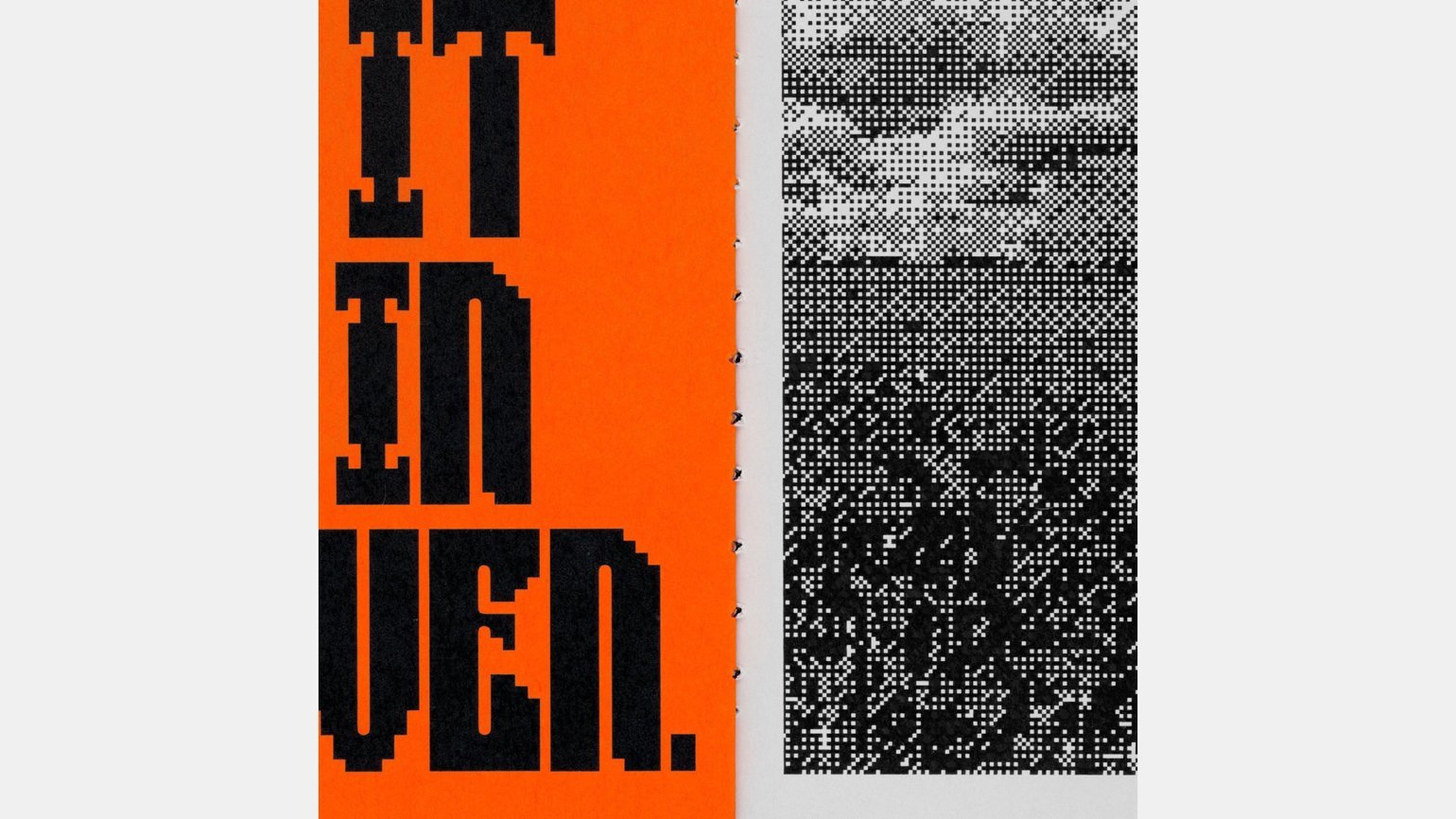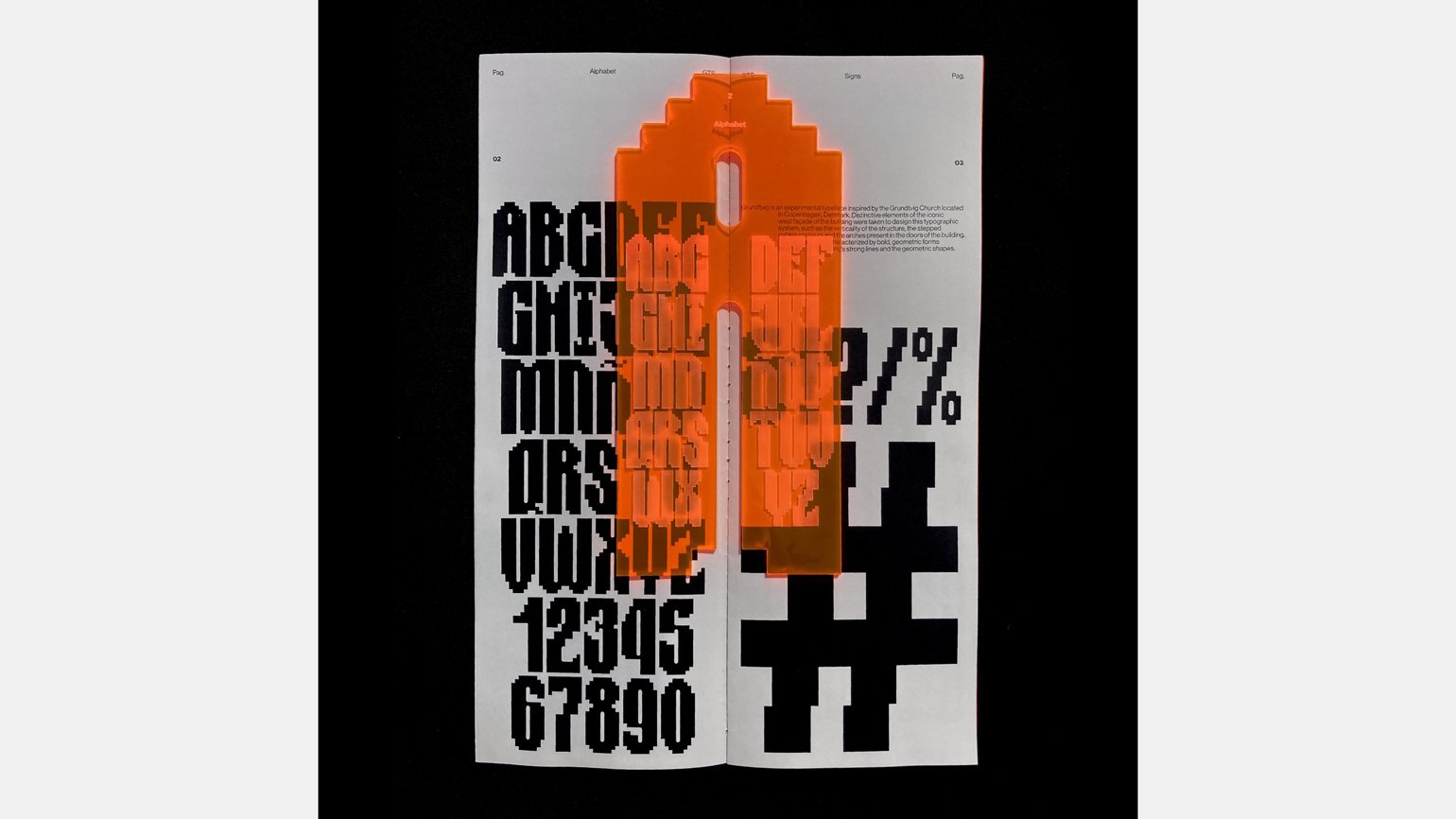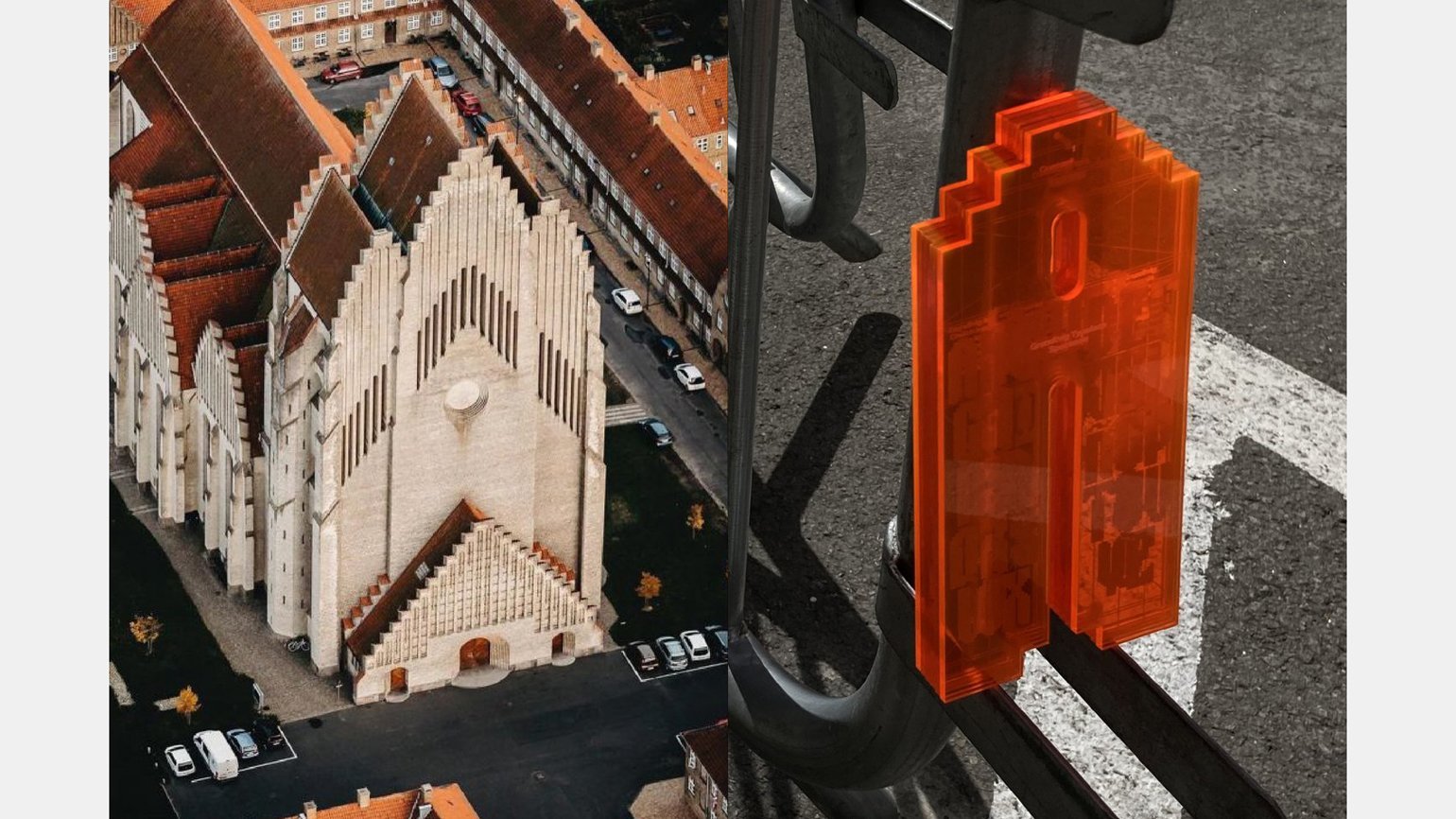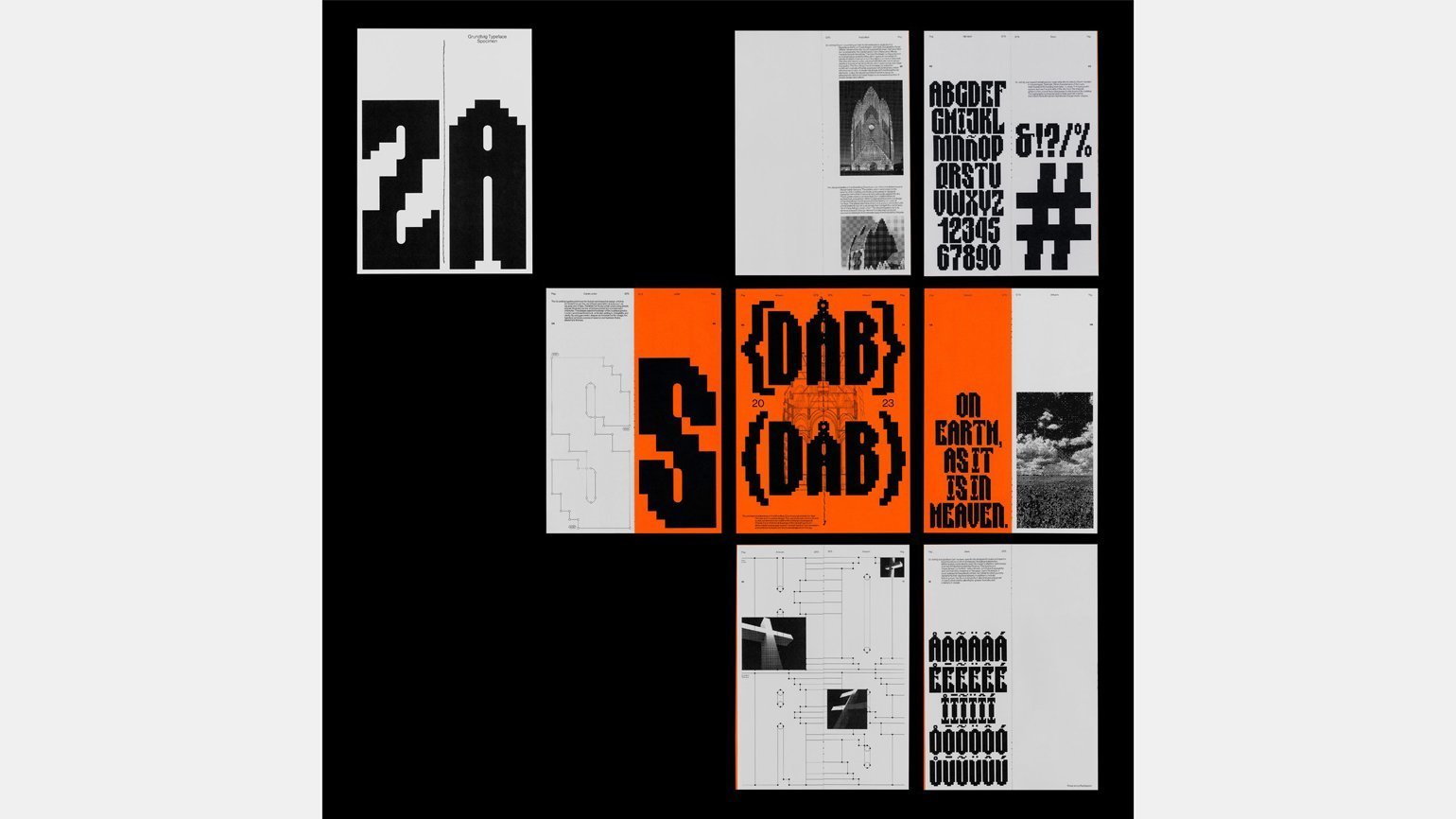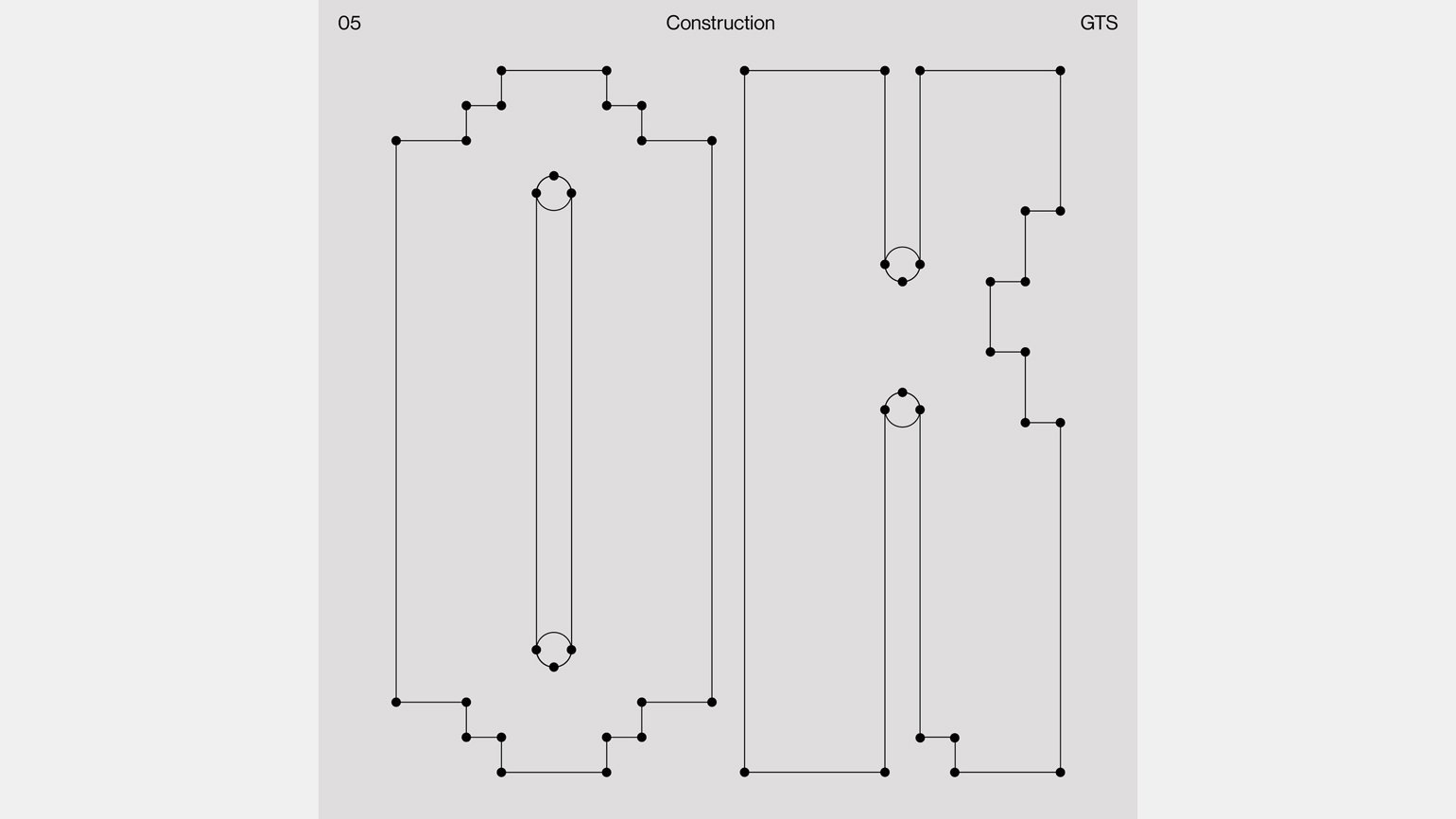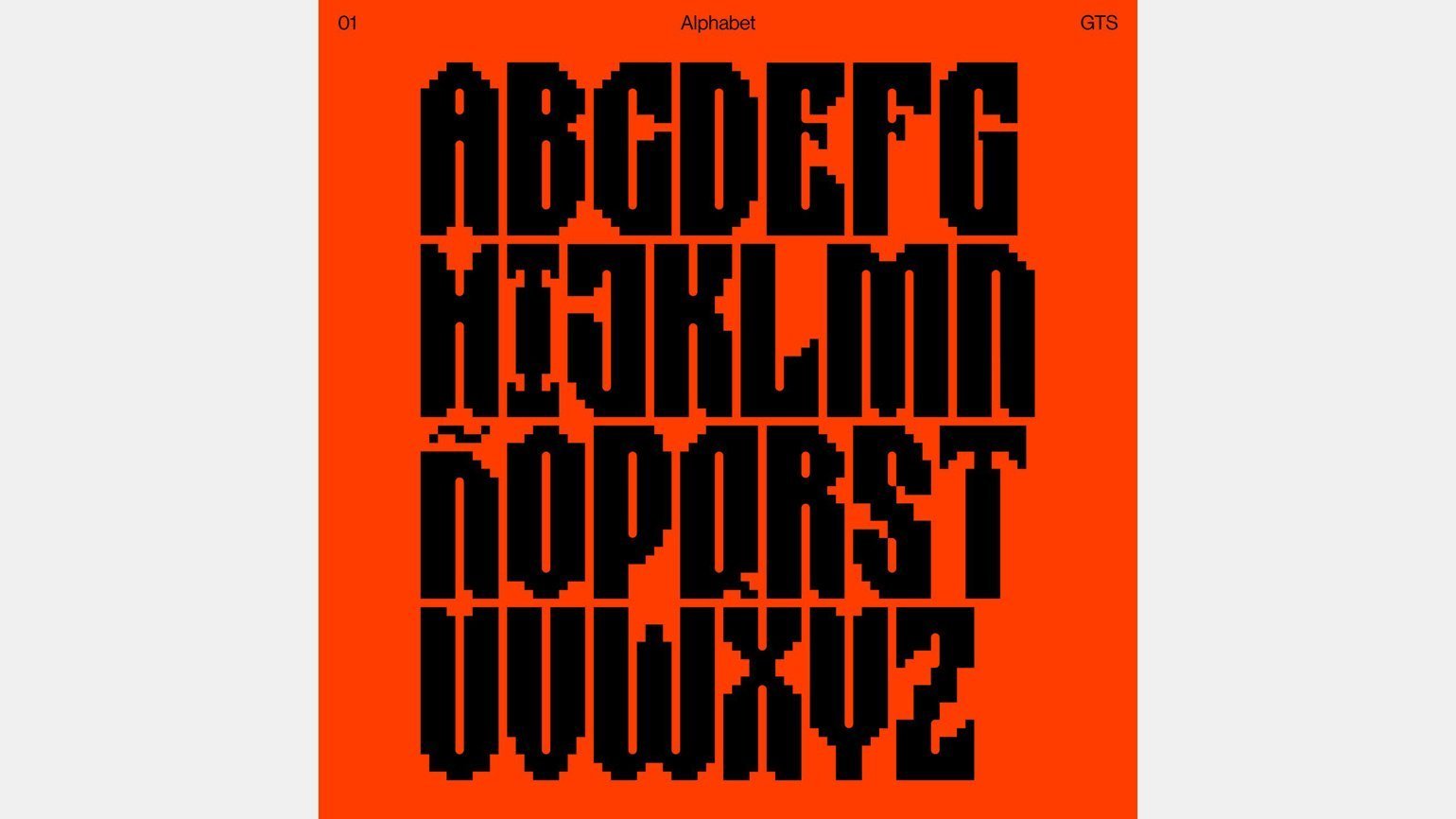
Дизайнер из Барселоны превратил формы церкви в шрифт
Он вдохновился геометричным фасадом и округлыми арками.
Графический дизайнер Рейнальдо Камехо сейчас учится в Школе дизайна и инженерии Барселоны. Он превратил в цифровой шрифт то, что, казалось бы, вряд ли может быть использовано подобным образом. Это Церковь Грундтвига в Копенгагене. «Я не особо ей интересовался, это случайность, — рассказывает Рейнальдо. — Нам нужно было создать типографику [в качестве итоговой работы курса] на основе некоторых зданий с интересной архитектурой, и в результате розыгрыша я получил Церковь Грундтвига». Рейнальдо делал набросок за наброском, пока ему не пришло в голову отразить в шрифте силуэт самой церкви.
Шрифт Grundtvig
«Церковь Грундтвига — невероятное здание, оно сочетает в себе классические черты и яркие геометрические формы, меня это восхищает, — говорит Рейнальдо. — Я выделил два характерных элемента его фасада — вертикальность и ступенчатые контуры». Рейнальдо включил кривые в свой дизайн, чтобы смягчить прямые линии и углы. Он использовал форму дверных арок для контрформ букв. «Обычно я сначала работаю в Adobe Illustrator, а когда я уже нарисовал все символы, я переношу их в Glyphs, чтобы создать шрифт и настроить пробелы, — говорит Рейнальдо. — Но шрифт Grundtvig моноширинный, поэтому всё намного проще».
Шрифт Grundtvig
Дизайнер не ограничился только двухмерной плоскостью: он также создал 3D-изображение буквы А. «Я хотел, чтобы оно имитировало форму фасада», — говорит дизайнер. В журнале It’s nice that замечают, что шрифт напоминает пиксельные картинки в Nokia 3310. А дизайнер больше всего хочет, чтобы его шрифт использовали в церкви.
Шрифт Grundtvig